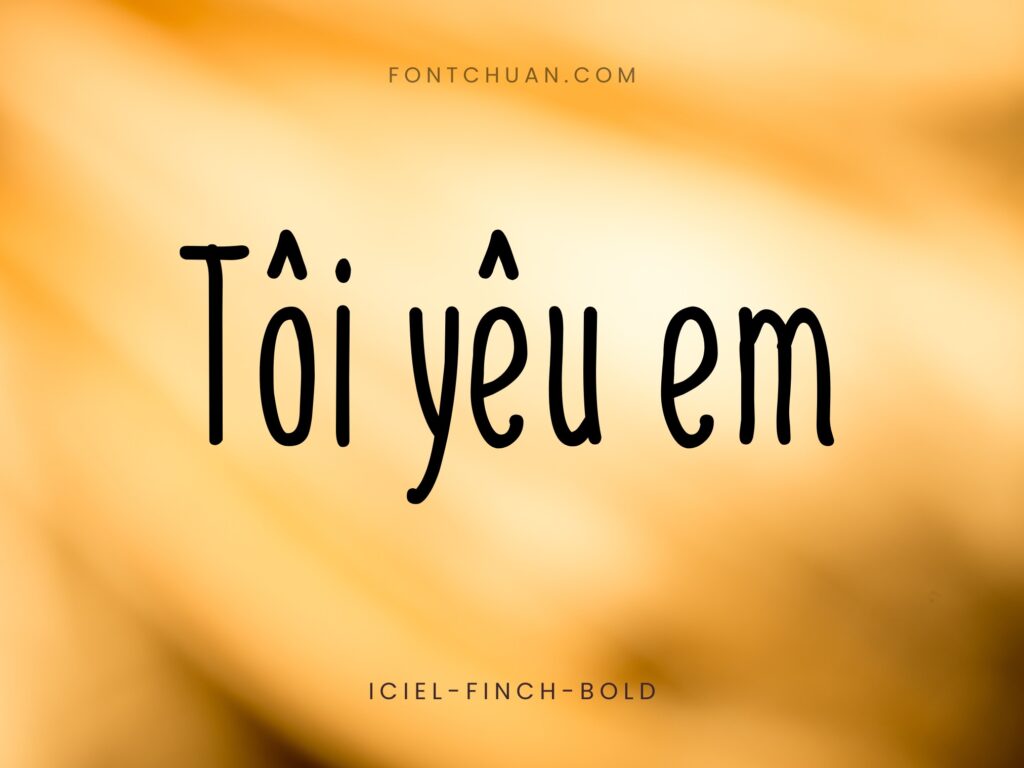
Font iCiel Finch Việt Hóa
Việt hóa bởi: Iciel
Finch là một kiểu chữ monoline script tinh tế, được thiết kế bởi Omotu Studio. Font này mang phong cách hiện đại với hai biến thể: sạch sẽ (clean) và đóng dấu (stamped), tạo sự linh hoạt cho các dự án thiết kế. Đặc biệt, Finch đã được Việt hóa bởi Iciel, hỗ trợ tiếng Việt cùng nhiều ngôn ngữ khác, đáp ứng nhu cầu đa dạng của người dùng. Thành viên của Font Chuẩn đã sưu tầm và chia sẻ font này, giúp cộng đồng thiết kế ứng dụng dễ dàng trong các dự án của mình.
Về đặc điểm thiết kế, Finch sở hữu các đường nét mượt mà và đồng nhất, tạo cảm giác thanh lịch và chuyên nghiệp. Font này phù hợp cho các thiết kế như logo, tiêu đề, thiệp mời, bao bì sản phẩm và các ấn phẩm truyền thông xã hội. Ngoài ra, Finch còn thích hợp cho các ngành nghề như quảng cáo, ẩm thực, thiệp cưới và spa, cùng các sự kiện đặc biệt như lễ hội, sinh nhật, Valentine và Trung thu.